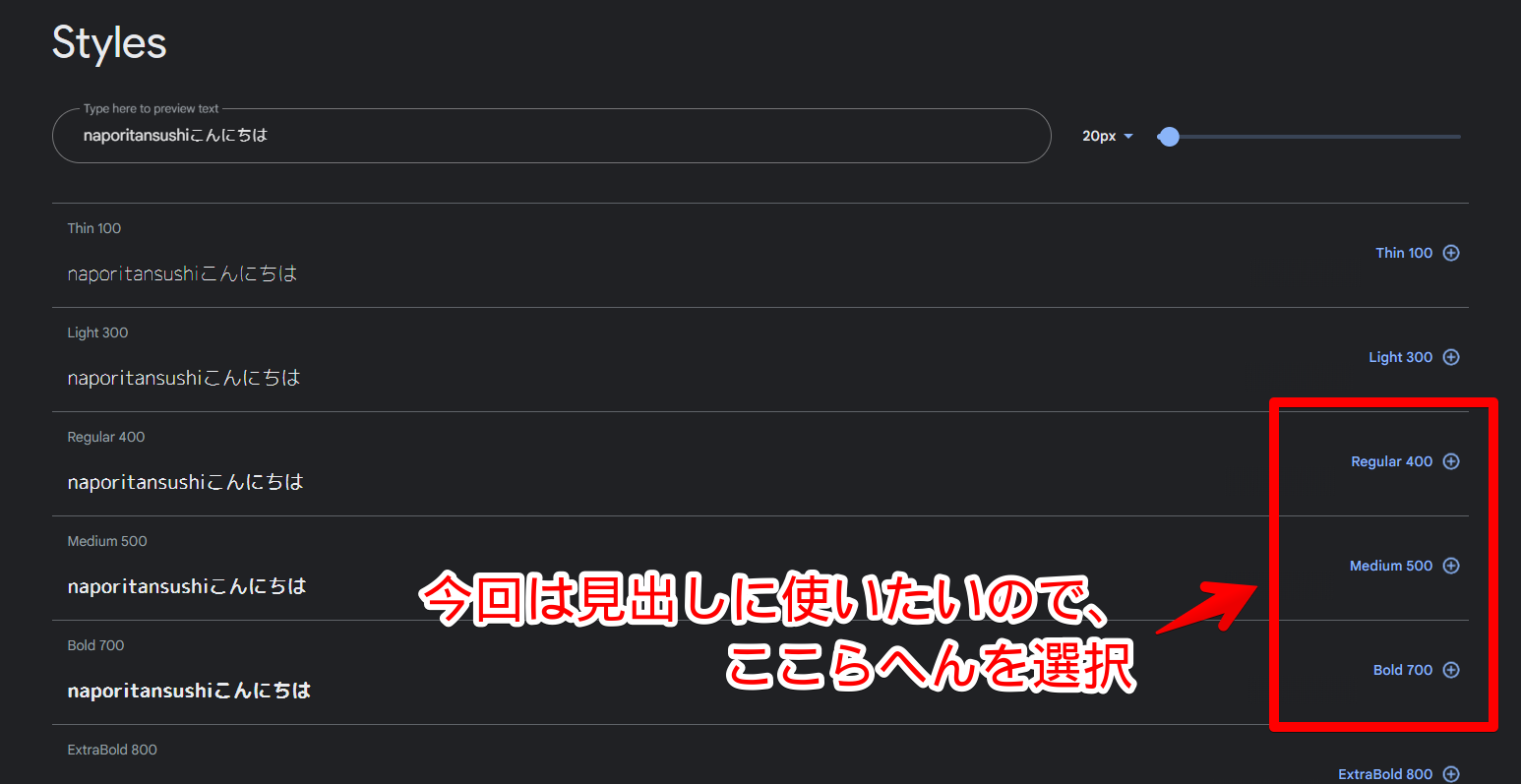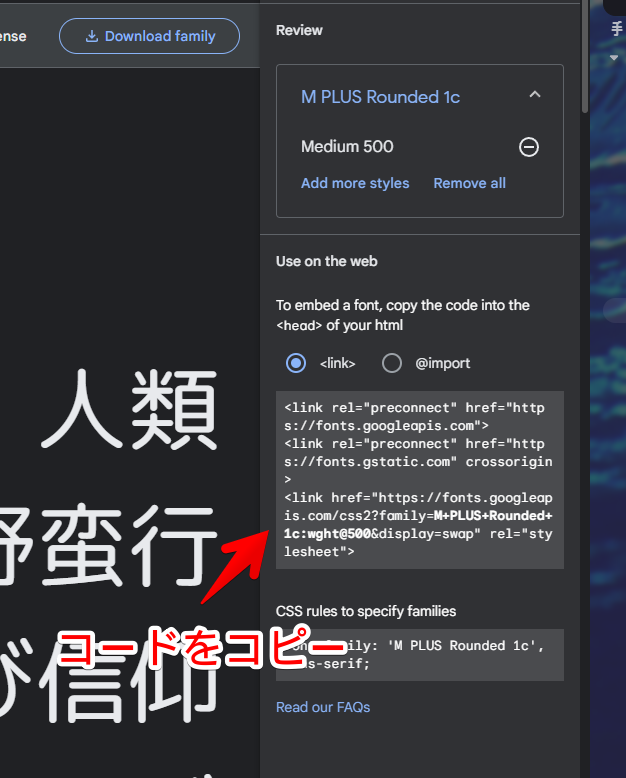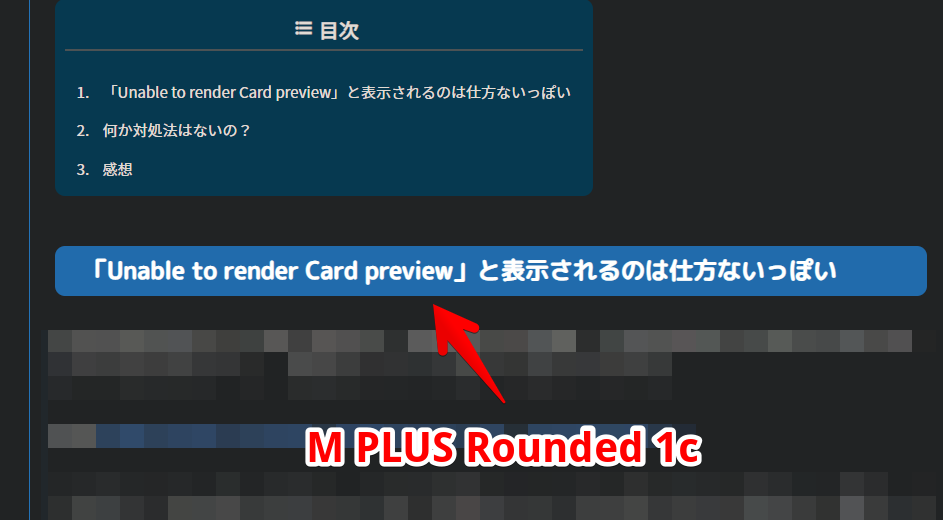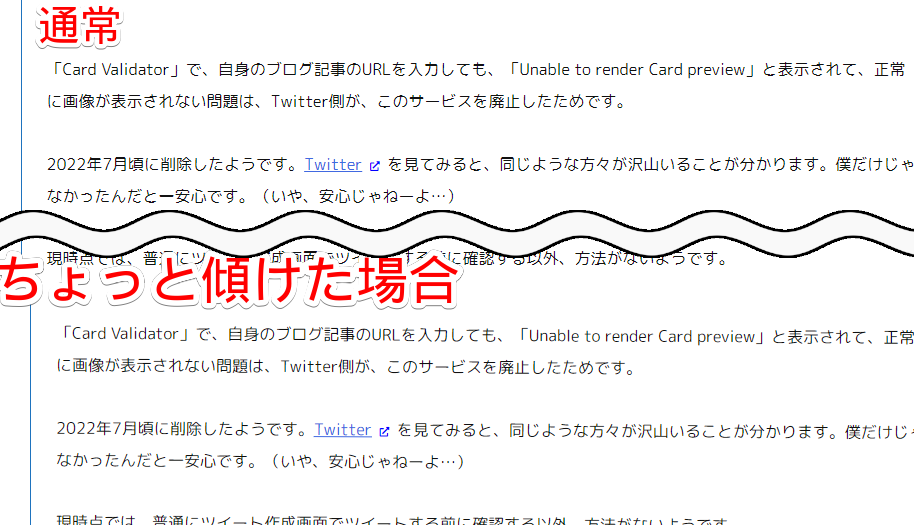
読者の方に言われてつなぎゴシックやKosugi Maruを使うことにした話
この記事では、デザインつよつよの読者さんに教えていただいて、サムネイルとYouTube動画の字幕を変えたという話について書きます。
ブログのフォントに「Kosugi Maru」、サムネイルに「つなぎゴシック」、YouTube字幕に「モボ」を使うことにしました。
読者の方に言われてつなぎゴシックやKosugi Maruを使うことにした話
そんな中、デザインつよつよの読者さんからたっぷりのご指摘をいただきました。サムネイルの文字が細いYouTubeの字幕がグネグネで見にくい…などなどです。
僕はデザイン力が皆無かいむです。どれが見やすいかすら分からないぺーぺーです。今までもこだわりが一切なく適当に選んでいました。
たしかに見返してみるとどれも適当で見にくかったです。「このままではいかん!」と思いデザインつよつよの読者さんに聞いて色々勉強させていただきました。
まとめ
現時点では以下のような状況になっています。
つなぎゴシックブログのサムネイル画像に利用
Kosugi Maruブログのベースフォント(本文、見出しなどなど)に利用
Noto Sans JPブログの本文に利用していたが、2022年11月30日以降「Kosugi Maru」に変更
M PLUS Rounded 1c当初ブログの見出しに使っていたが、2022年11月30日以降「Kosugi Maru」に完全移行
モボYouTubeの字幕に利用
源暎エムゴもしかするとYouTubeの字幕に登場するかもしれないが今のところ利用予定なし
主にGoogle Fontsの「小杉丸(Kosugi Maru)」を使っています。
僕が好きな角丸処理された可愛らしい文字で好きです。
「M PLUS Rounded 1c」や「Kosugi Maru」のあれこれ
最初は小杉丸(Kosugi Maru)を検討していた
当時、指摘してくださったデザイン読者様からいくつかの「これおすすめ」ってフォント候補を提示していただきました。
その中にGoogle Fontsの「Kosugi Maru」があったのですが、いざブログ本文に導入してみると英語(アルファベット)の文字間隔が狭くなって見にくい結果になりました。
「ナポリタン寿司のPC日記」の本文を「Kosugi Maru」にしたら英語が見にくくなっている画像
読者様からも「あ~それならなしだね」という意見だったので残念ながらやめていました。
結局こちらで書いているように最終的には再びKosugi Maruに戻りました。
「M PLUS Rounded 1c」も検討していた
Kosugi Maruと同様角丸処理されて僕のドンピシャ好みの「M PLUS Rounded 1c」も案としてだしていただきました。
実際使ってみると、見出し(h2やサイトタイトル)などのフォントサイズが大きい場合はうまく表示されるのですが、本文(pタグ)など一定フォントサイズ以下になった時、文字がギザギザ(ジャギー問題)になったのでやめました。
調べてみると当サイトだけではないようです。「M PLUS Rounded 1c」の仕様っぽいです。
transform:rotate(0.03deg)」のCSSで要素全体を微妙に傾けることで解決するらしいですが、「いやいや、なんでフォント変えるだけなのに全体を傾ける必要があるんだよ」と思いやめました。
いちお試した上でこれはなしなしってなりました。
ただし、ある程度文字サイズが大きい場所(見出し)にはちょーどいいと思い、見出しに適用していました。
結局最終的には見出しも「Kosugi Maru」にしたんですけどね。
しぶしぶ本文には「Noto Sans」にしていた
僕は角丸処理されたフォントが見た目的に好みだったので、できる限りブログの本文にも導入したいと思っていました。
しかし、上記に書いたように「Kosugi Maru」だと英語の文字間隔が狭く、「M PLUS Rounded 1c」だとジャギー(ギザギザ)問題がありました。
サムネイル(アイキャッチ画像)やYouTubeの字幕には問題なく導入できました。
本文はどうしよう…ということで結局これまでも使っていた「Noto Sans JP」をしぶしぶ継続利用していました。角丸じゃないので僕の完全な好みではないですが、安定です。
「ナポリタン寿司のPC日記」というサイトタイトルや見出しなど変えられる部分は角丸系フォントに変えていました。
最終的にKosugi Maru+Noto Sansの合わせ技を使うことにした
本記事を最初に公開したのが2022年9月でその2か月後の11月に気づきました。
「よくよく考えたらローマ字と日本語でフォント別々にできるじゃん」ってね。
以下のようにCSSを書いて、アルファベットを「Noto Sans」、日本語を「Kosugi Maru」にしています。
「Noto Sans」はどのブラウザでも安定して綺麗に表示されるので悪くなかったのですが、やっぱり僕の好きな角丸加工されている「Kosugi Maru」のほうが好みだったので一番目に入るブログ本文に適用できて良かったです。
「ナポリタン寿司のPC日記」ブログのフォントを「Noto Sans JP」から「Kosugi Maru」にした比較画像
font-family: 'Kosugi Maru';」だけだと英語にも日本語にも適用されてしまいますが、合わせ技で最初に「Noto Sans」を書くことで、英語に関してはそっちが優先になり日本語に関しては後者が採用されるようになります。
ここらへんの詳しい仕組みはド初心者の僕には分かりませんが、僕はそういう風に捉えています。優先させたいフォント、英語のフォントを先に書く…ってね。
Kosugi Maru
現時点で僕がブログに採用しているフォントです。
つなぎゴシック
mokuzai(木材)」さんという方が作成したフォントです。「Zen角ゴシックN」フォントを角丸・すみだまり処理したフォントで仮名を太く90%に小さくしている点が特徴です。
サンプル画像を貼っておきます。
ナポリタン寿司が作成した「つなぎゴシック」フォントのサンプル画像
綺麗すぎじゃね!?(笑)
今までフォントにこだわってなかった僕からすると驚きです。太文字っていいですよね。見やすい。よく見たら気づきますが、ひらがなと漢字の大きさが若干違います。漢字のほうが大きくてひらがなが小さいです。
モボ
フロップデザインフォント」が提供しているフォントです。「源ノ角ゴシック」に角丸処理を施したのが特徴です。有料の「モガ」フォントに合うように作成されたようです。
フリーフォントだと「バナナスリップ」、「モボ」、「つなぎゴシック」、「源暎エムゴ」、「さつき源代明朝」あたりを入れておけば間違いないとのことです。
こんなにフリーで見やすいフォントがあるのに、僕はなんで「ロゴたいぷゴシック-コンデンスド」や「鉄瓶ゴシック」といった独特なフォントを使っていたんだろうと不思議です。
別に上記2つのフォントが悪いわけではないです。
個性を出すには便利なフォントだと思います。ただ、一般的に見やすいかと言われれば微妙です。もぅ数百記事を書いているので手遅れ気味ですが、今の時点で指摘を貰えて本当に良かったです。